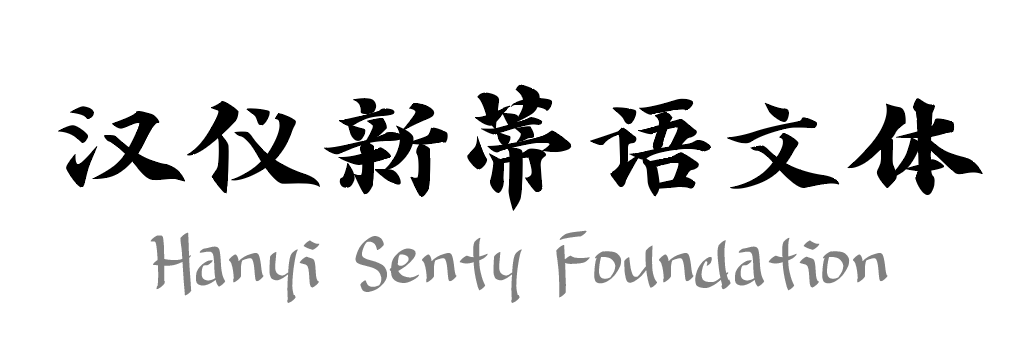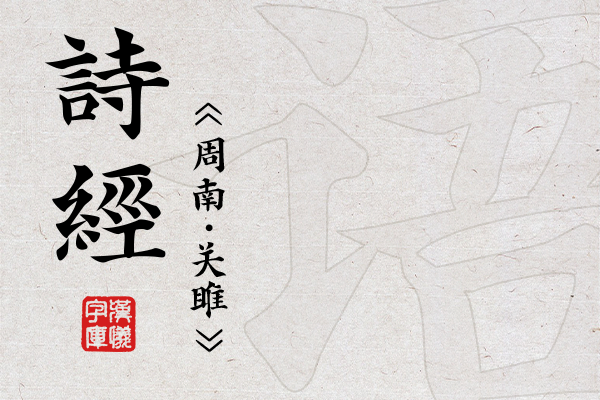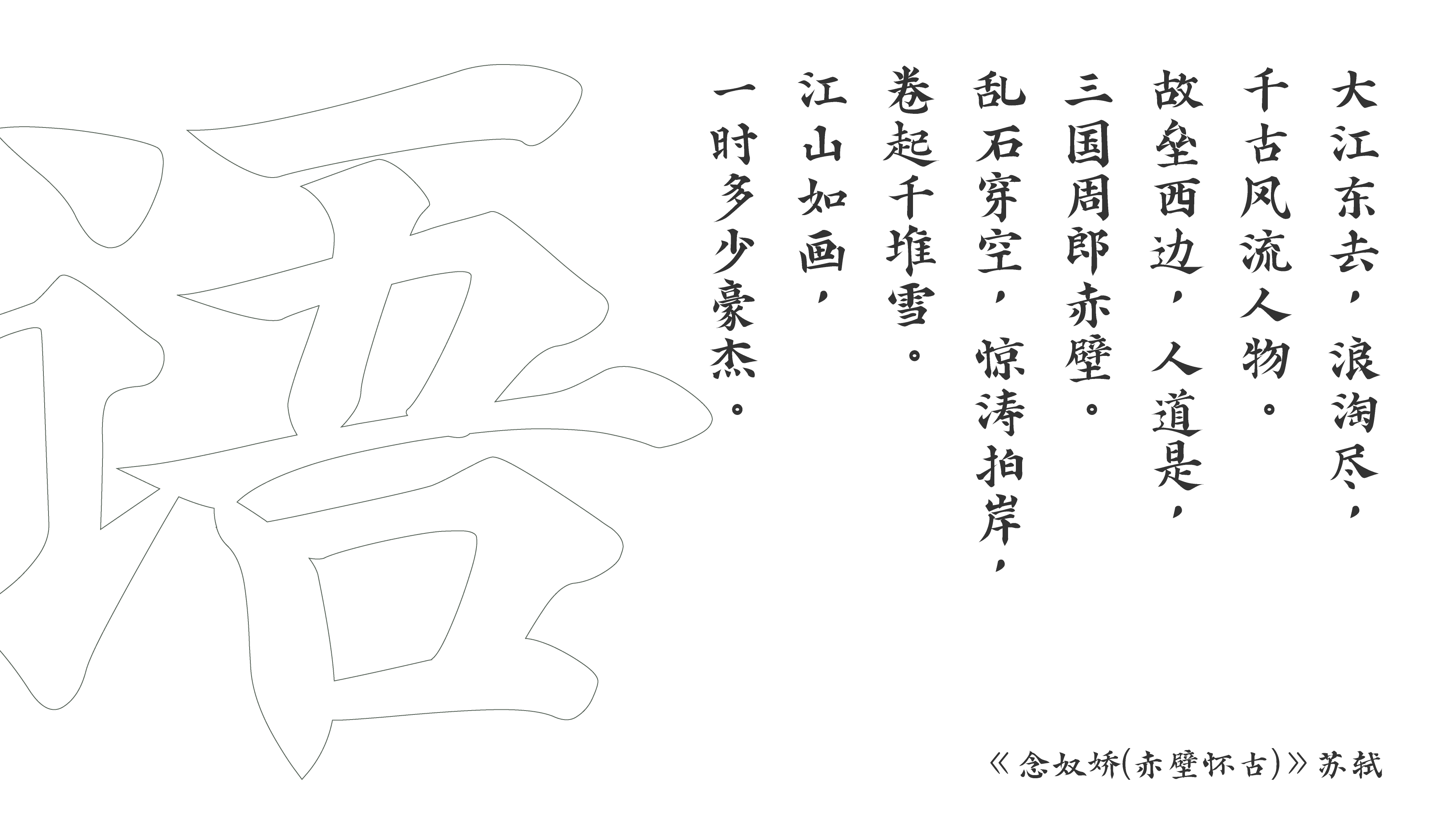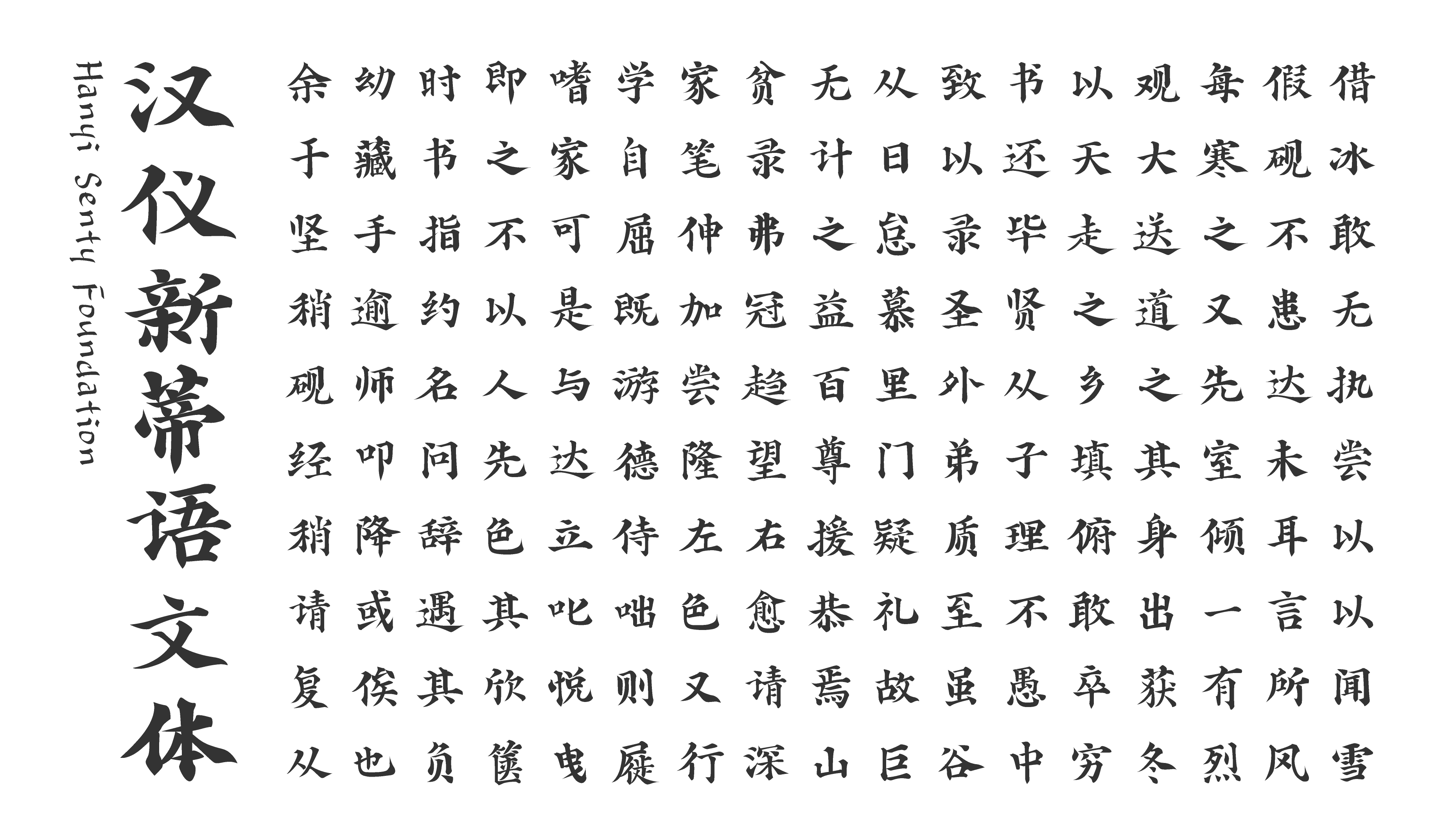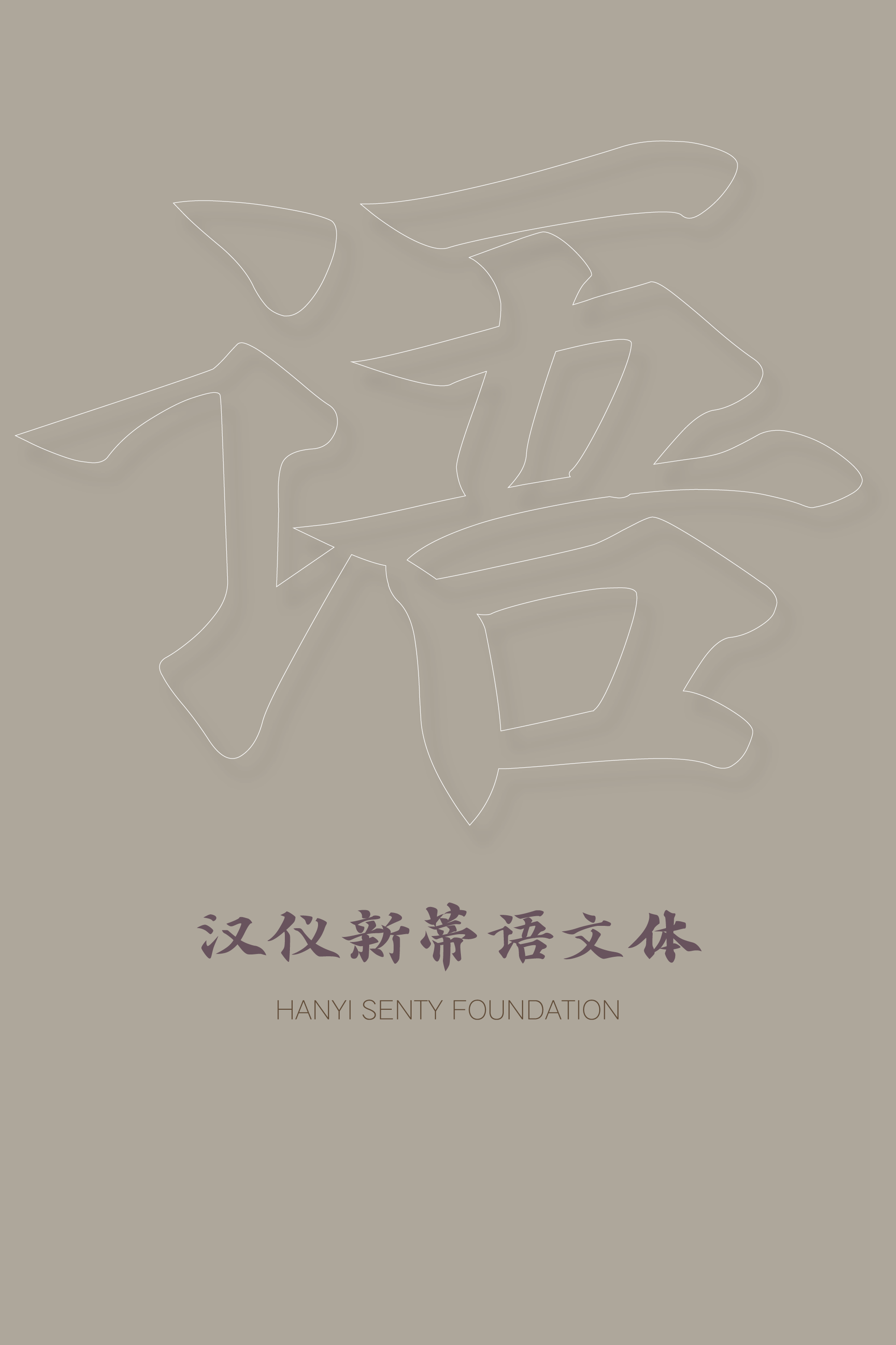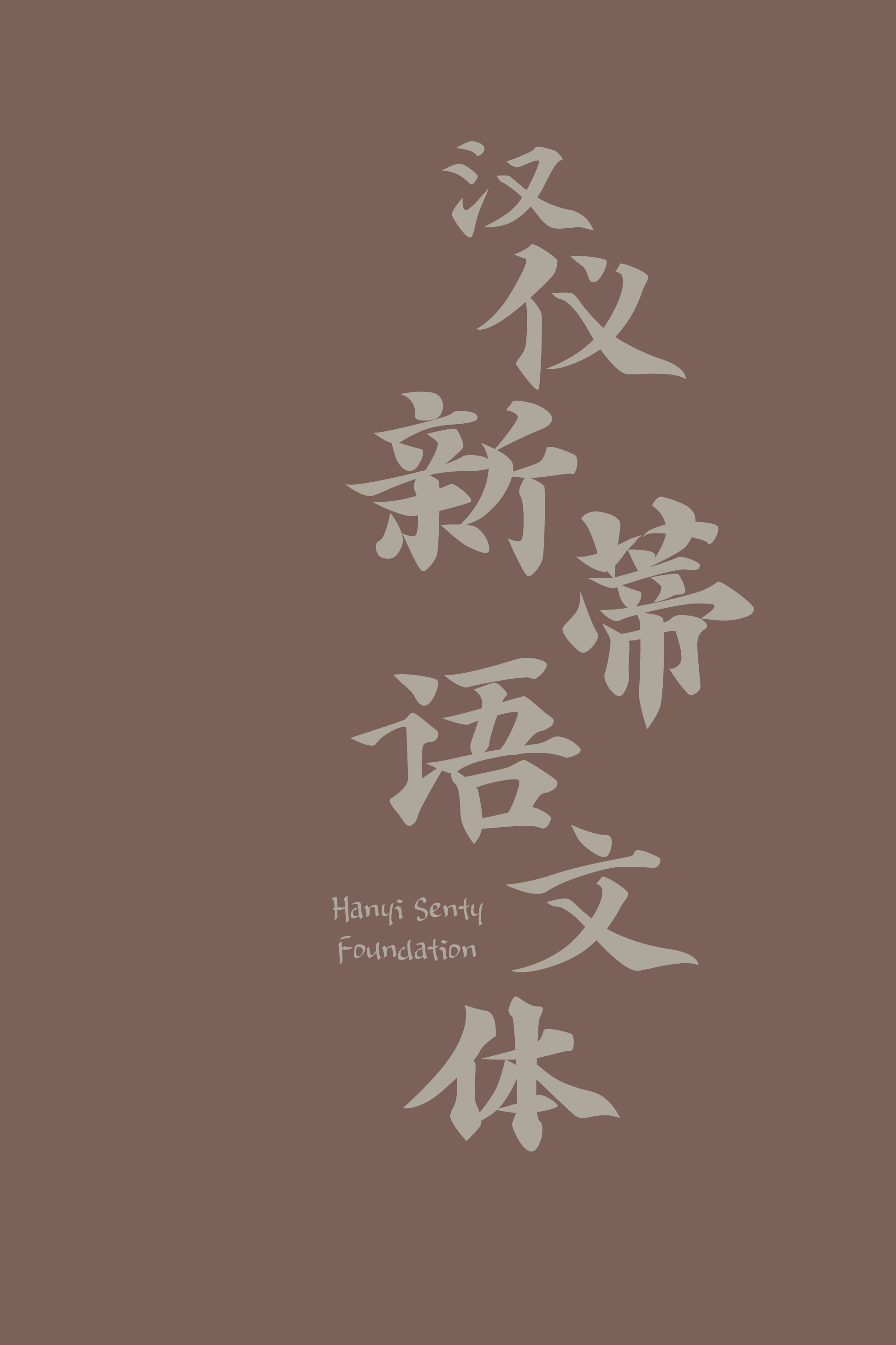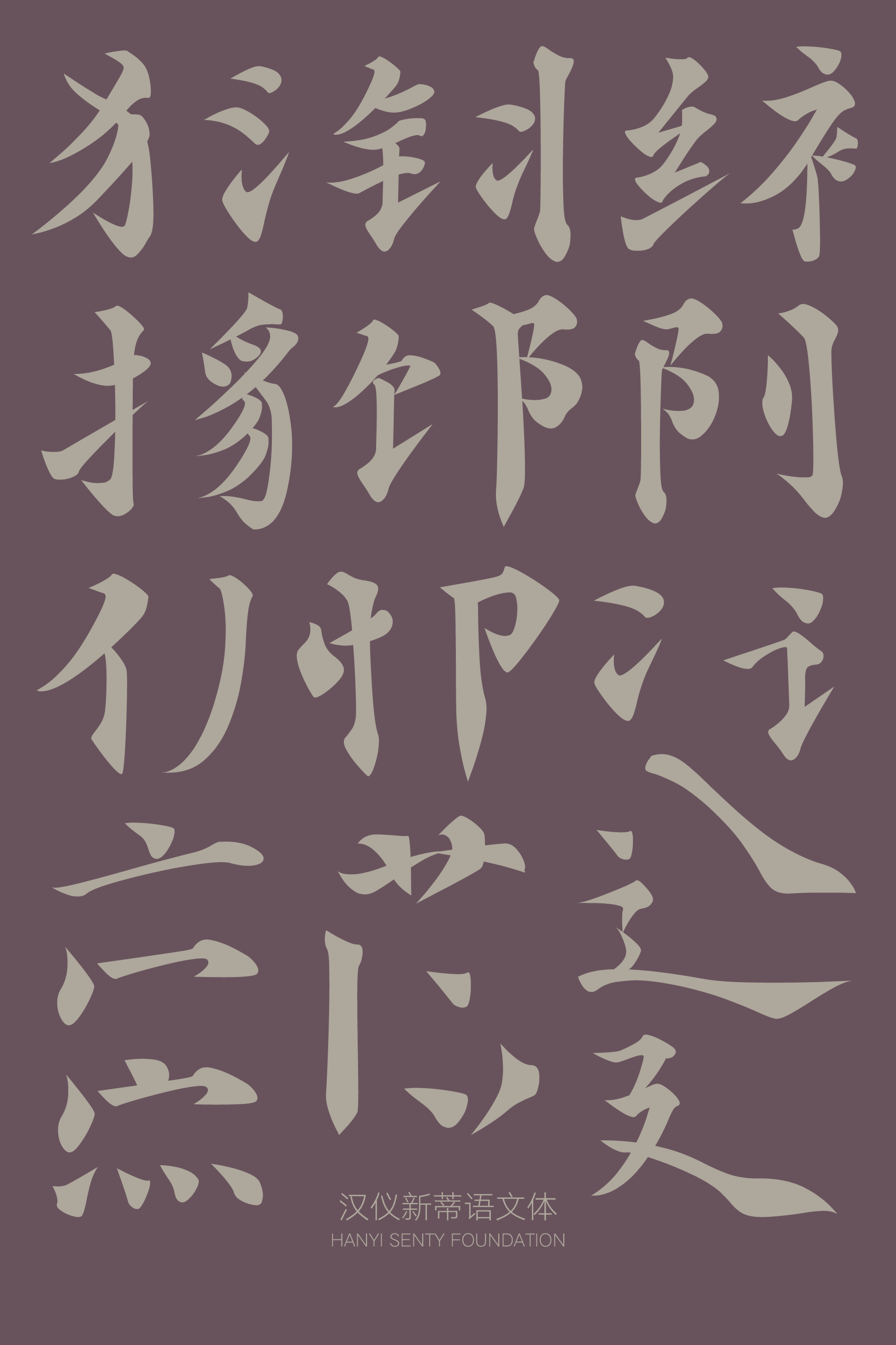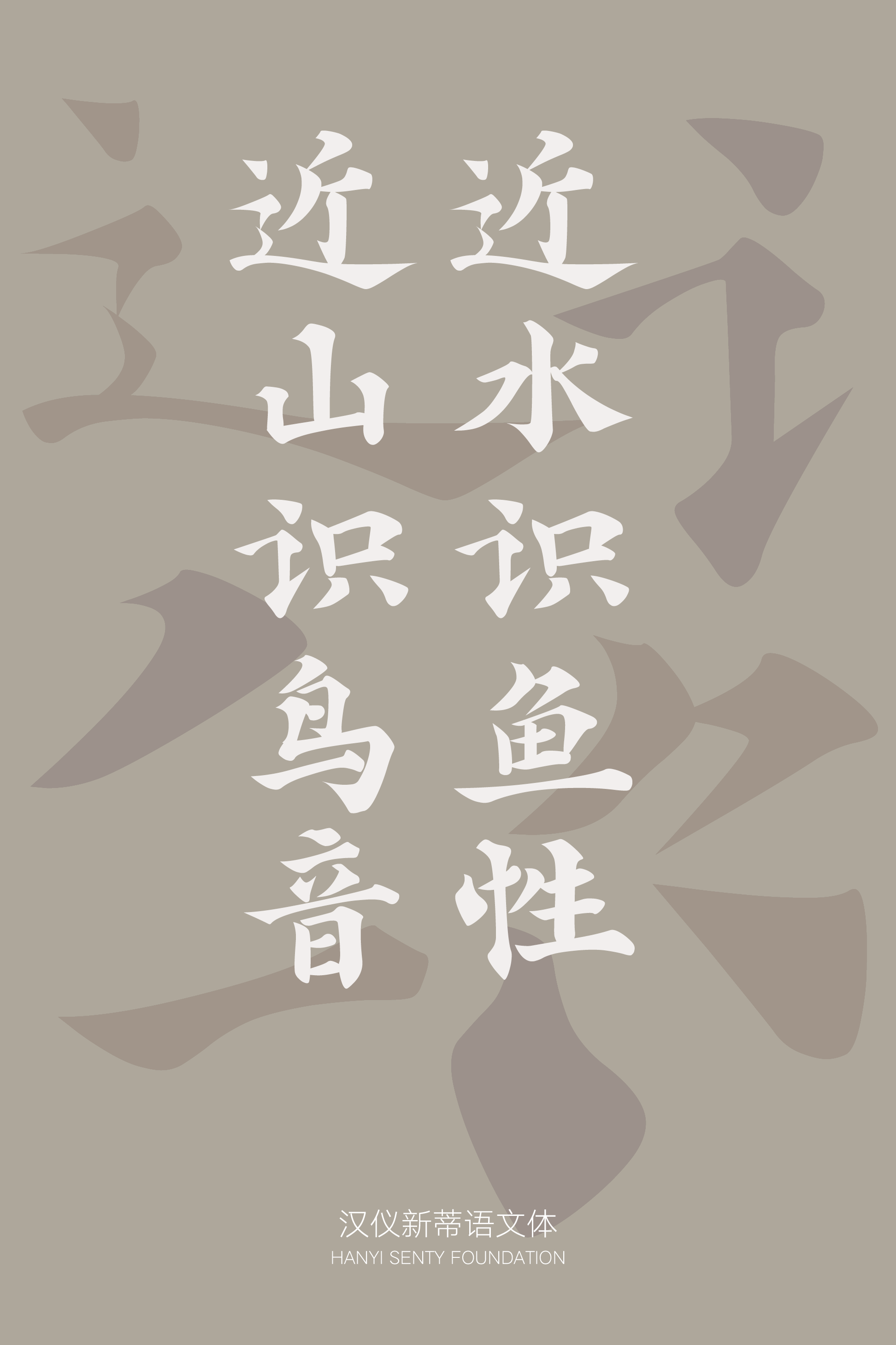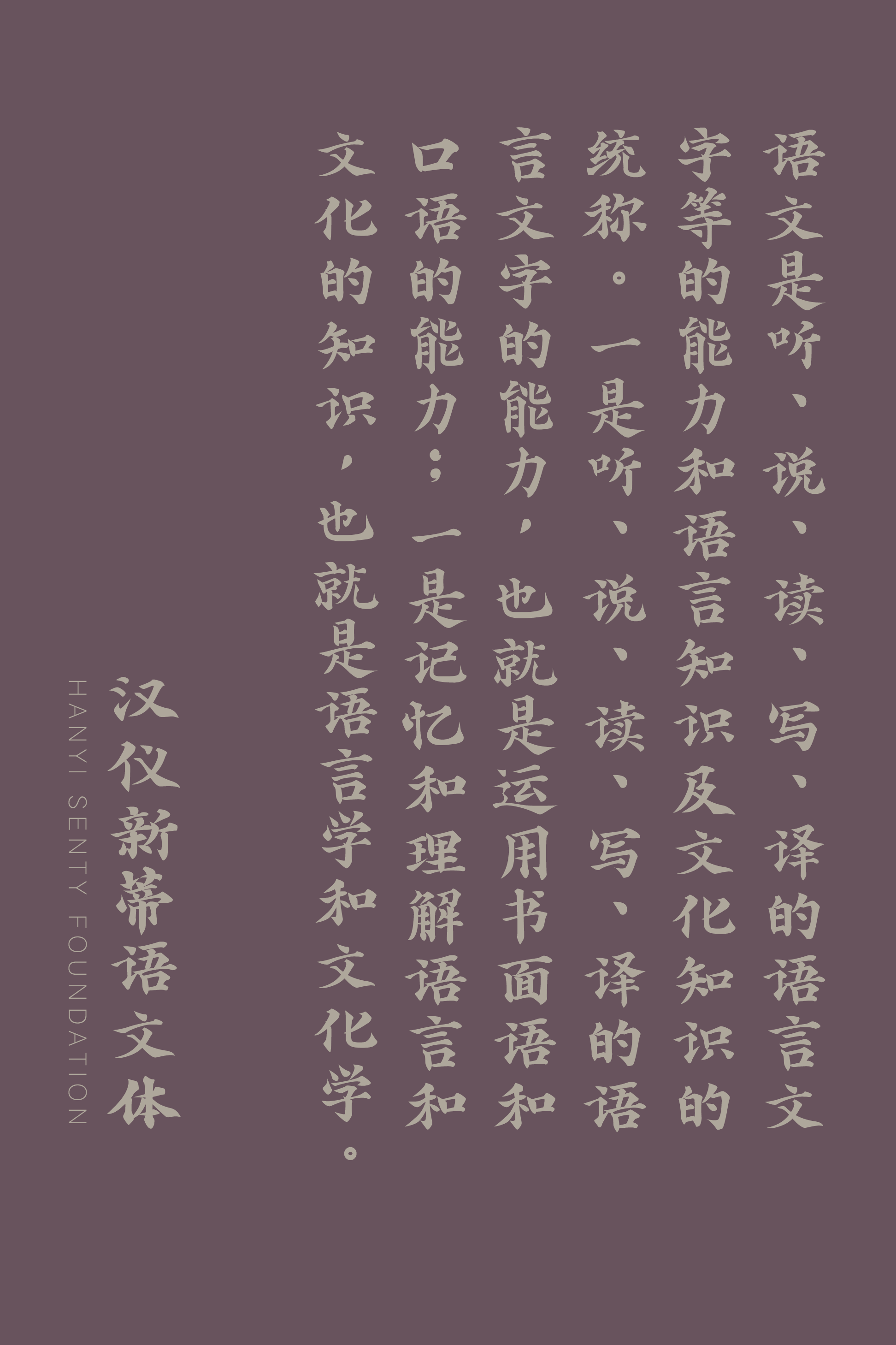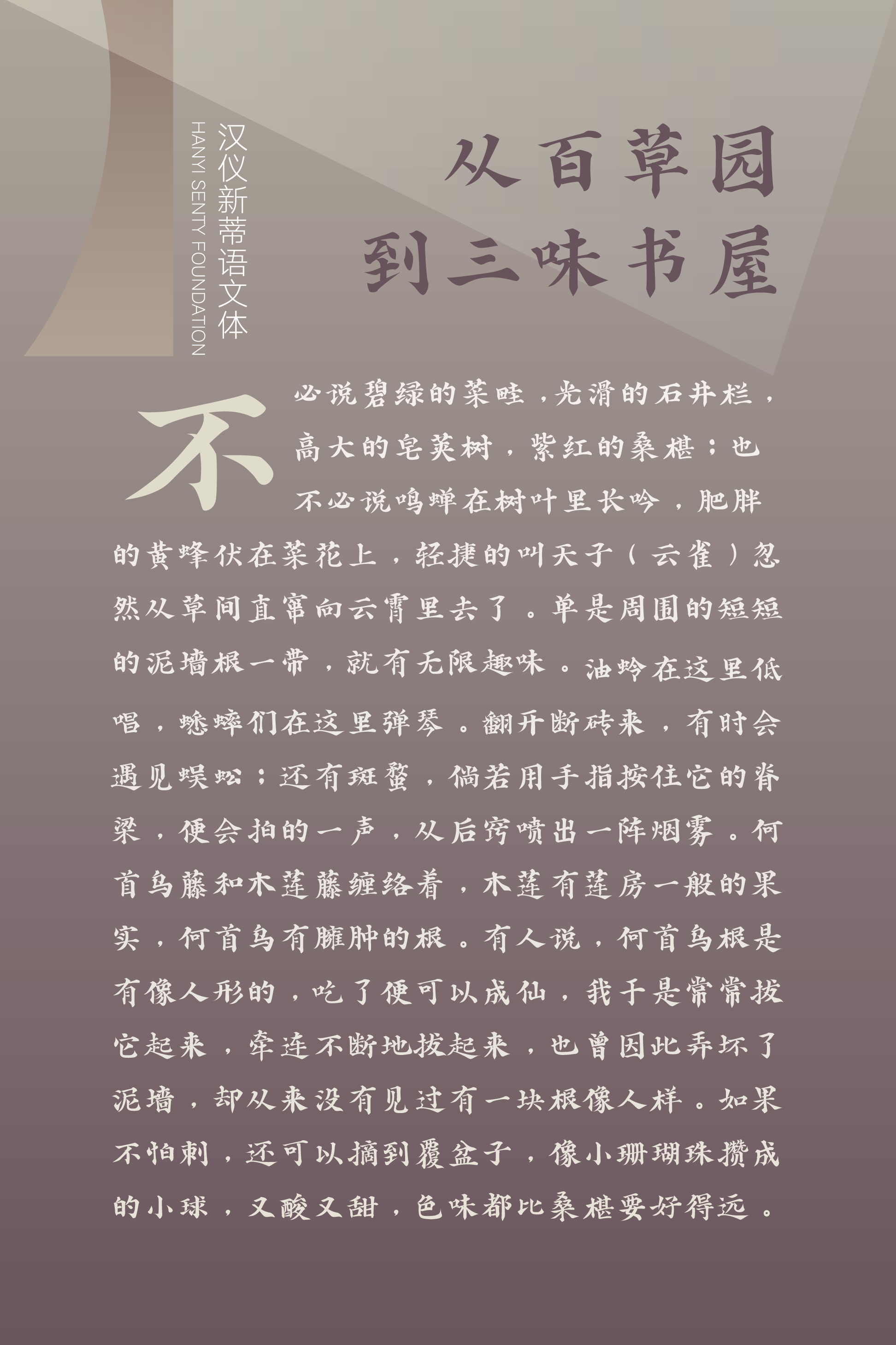
汉仪新蒂语文体字体介绍,汉仪新蒂语文体字体设计思路
书写字体
古典 / 传统 / 规范 / 文雅 / 中国风
品牌 / 标志 / 广告 / 标题排版 / 书籍封面 / 产品包装
汉仪新蒂语文体 | 创作背景
目前市场上大多数用于识字、语文教学的字体都偏向部件化,逐渐脱离了真实书写工具,特别是传统毛笔的书写特点。因此本着为学生提供一款具有书写感且符合现代书写规范的参考字体,“汉仪新蒂语文体”应运而生。
汉仪新蒂语文体 | 字体特点
汉仪新蒂语文体参考了近代以来一系列手绘语文教材的书法风格,并按照现代书写标准和规范重新设计制作。使得学生在识字、练字的同时,体会传统书写的魅力。
汉仪新蒂语文体 | 排版效果
汉仪新蒂语文体 | 字体海报